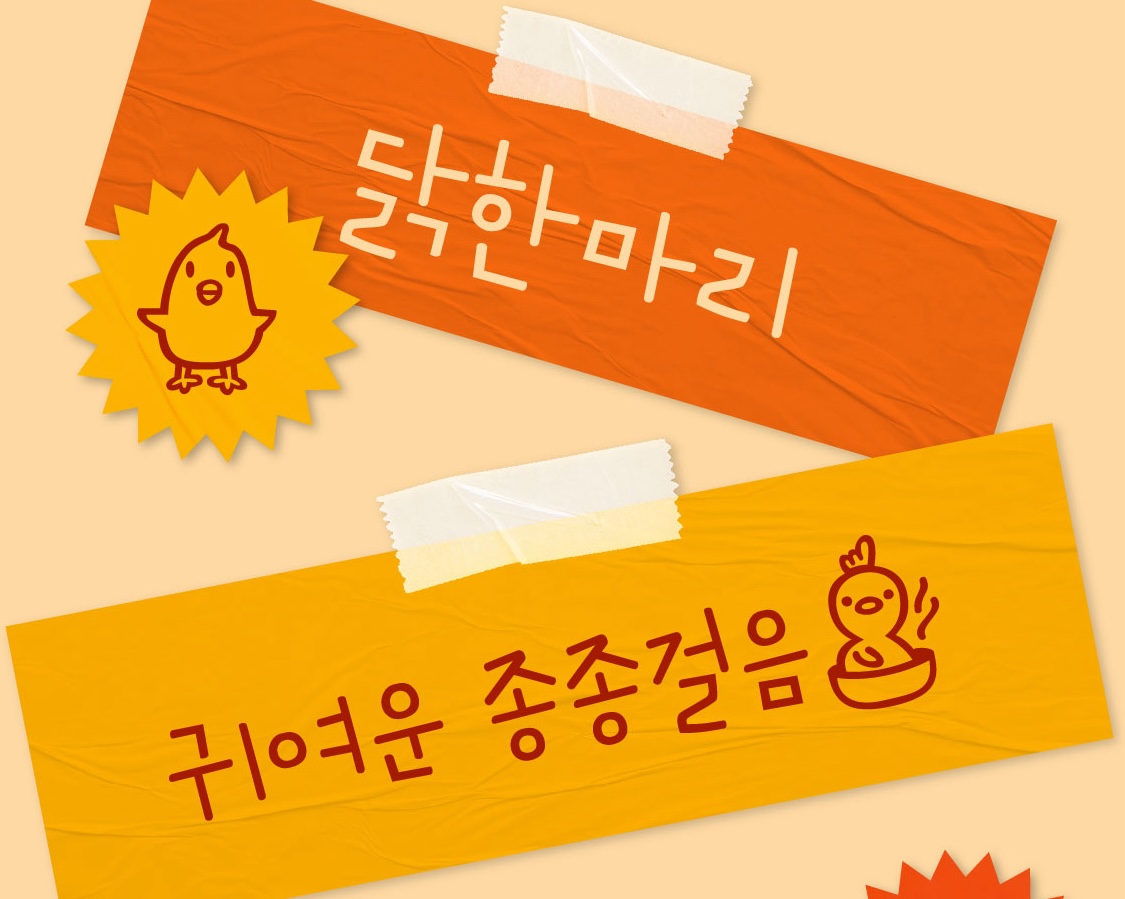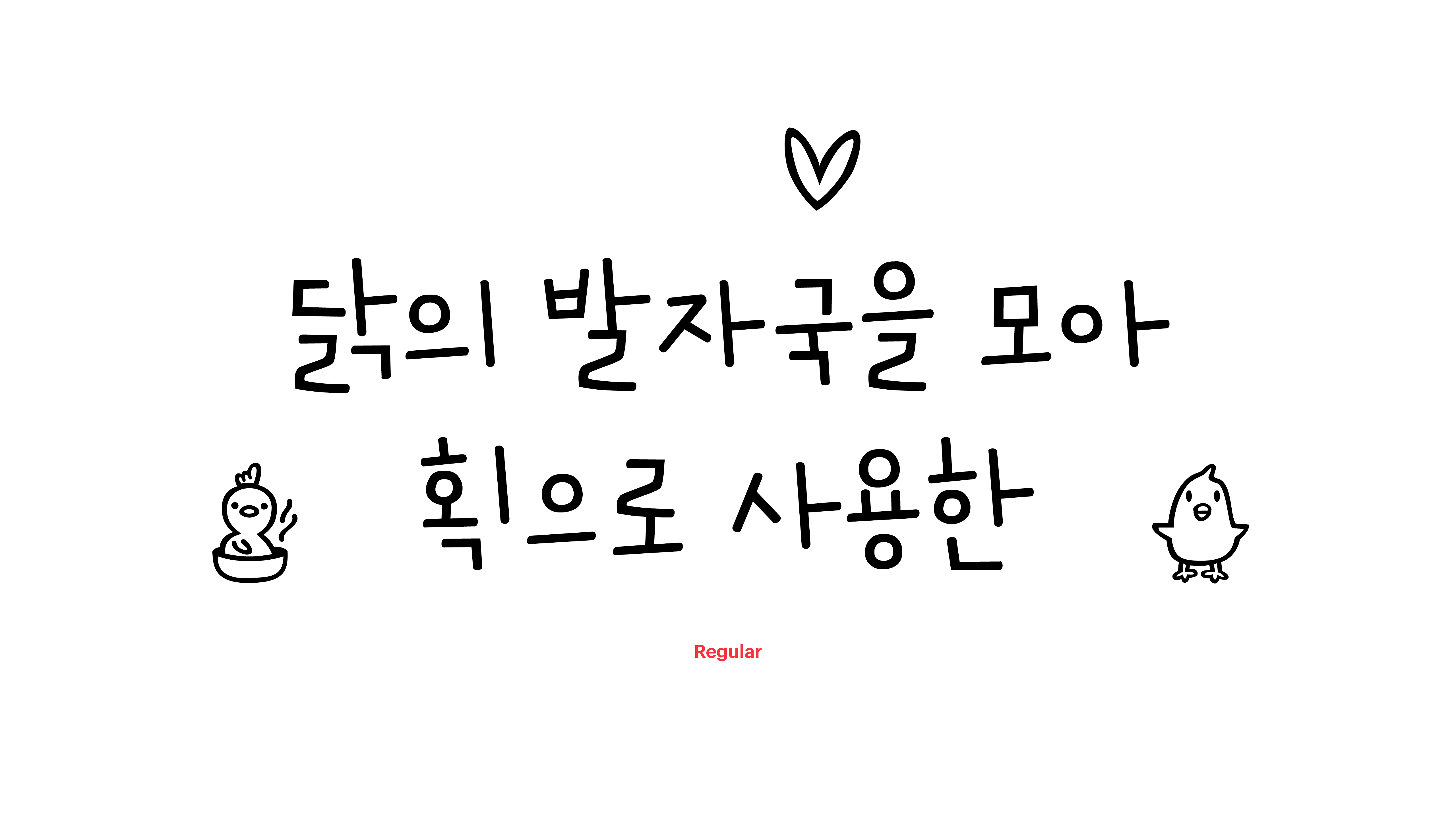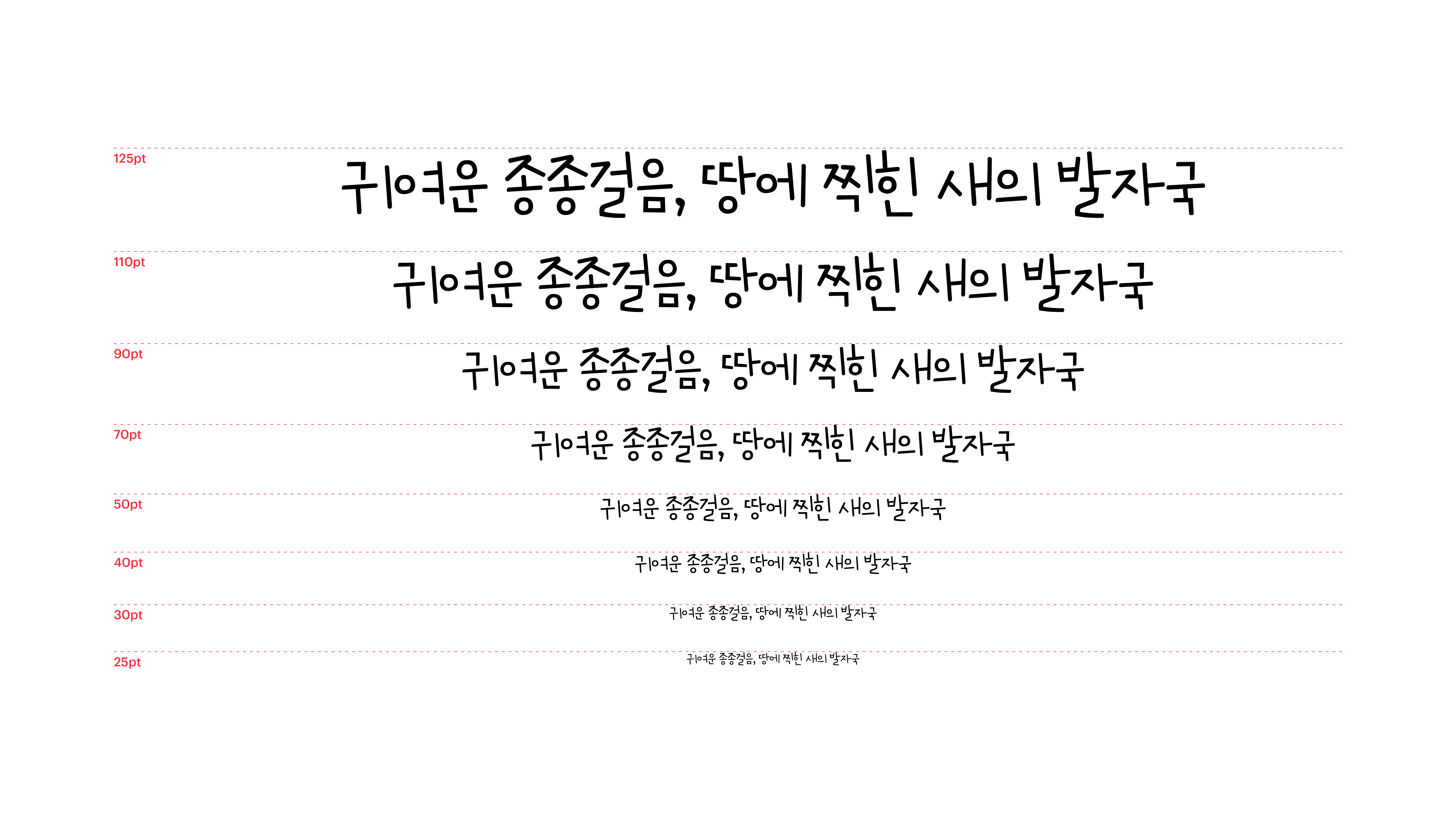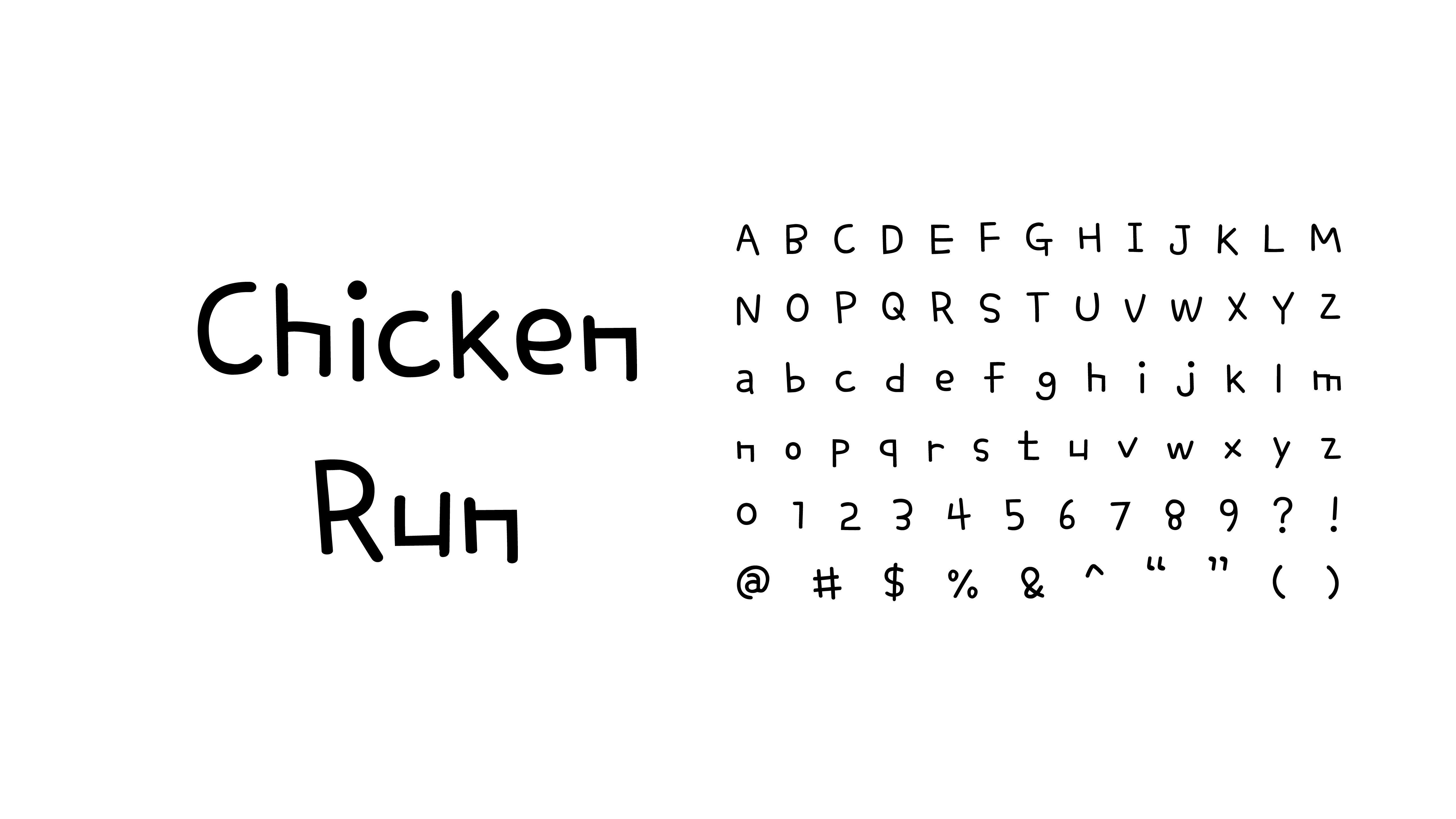
동물의 발자국은 제각각 매력이 다르지만, 새의 발자국은 어쩐지 가느다란 나뭇가지를 떠올리게 합니다. 닭한마리체는 우리와 가장 친근한 조류 친구! 닭의 발자국을 모아 획으로 사용한 것처럼 작고, 아기자기하지만 자유로운 감성을 지니고 있지요. 언제 또 다른 한 마리 새가 되어 훌쩍 날아갈지 모르는 이 폰트. 아끼지 말고 여기저기 많이 사용해주세요!